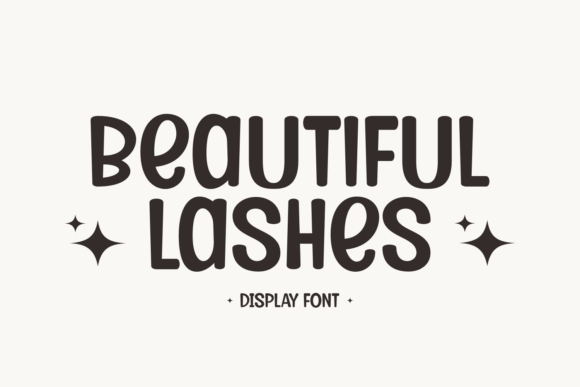
Beautiful Lashes
Beautiful Lashes – A Fonte que Transforma Qualquer Projeto em Arte
Se você está em busca de uma tipografia que combine charme retrô com a energia de um doodle, a Beautiful Lashes Font chegou para ser a sua nova aliada criativa. Essa fonte manuscrita traz um visual playful e bubbly que se destaca em logos, estampas e tudo que precisa de um toque divertido e moderno.
Por que a Beautiful Lashes é a escolha certa?
- Estilo único e versátil: combina traços grossos e sólidos com a leveza de uma escrita à mão, ideal para comic styles, cartoons e stickers.
- Aplicação ilimitada: funciona perfeitamente em camisetas, cartões de felicitação, tote bags, scrapbooks, capas de livros, wall‑art, menus de restaurantes e muito mais.
- Completa e pronta para uso: inclui maiúsculas, minúsculas, números e pontuação, atendendo a todas as necessidades de design.
- Temática sazonal: mantém seu visual atual em festas de Natal, verão, aniversários, Dia das Mães e outras celebrações.
Benefícios para a sua marca
Ao incorporar a Beautiful Lashes ao seu branding, você transmite:
- Personalidade cutesy e vibrante que atrai o público infantil e os amantes de design retrô.
- Coerência visual em diferentes materiais, de impressos a digitais.
- Diferenciação competitiva – poucos designers têm acesso a uma fonte tão divertida e ao mesmo tempo profissional.
Beautiful Lashes não é apenas mais uma fonte; é um instrumento de criatividade que eleva qualquer projeto a um novo patamar de originalidade. Seja para uma campanha publicitária, um presente personalizado ou um layout editorial, ela entrega magia visual em todas as estações. Experimente agora e veja sua marca brilhar com um toque de nostalgia contemporânea!